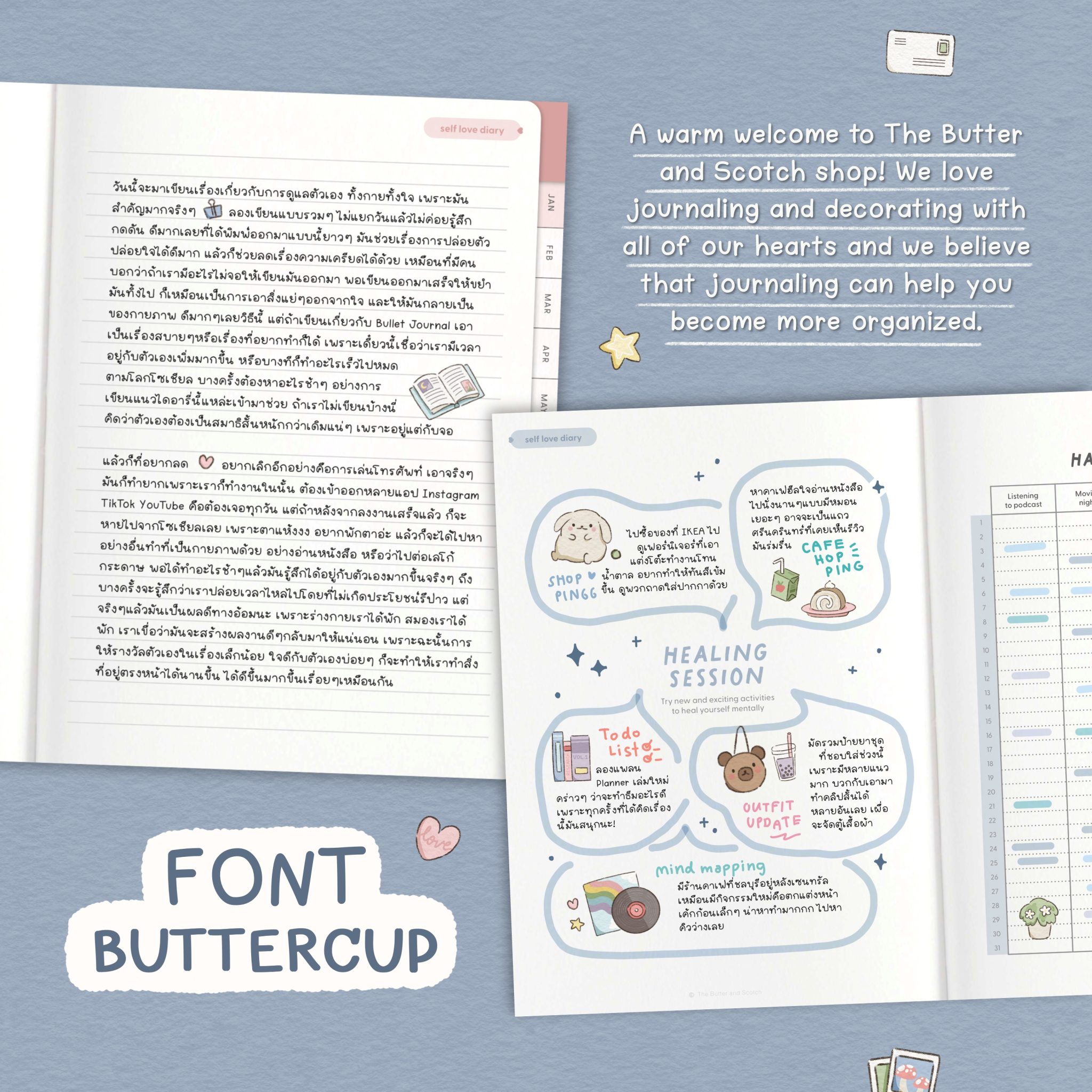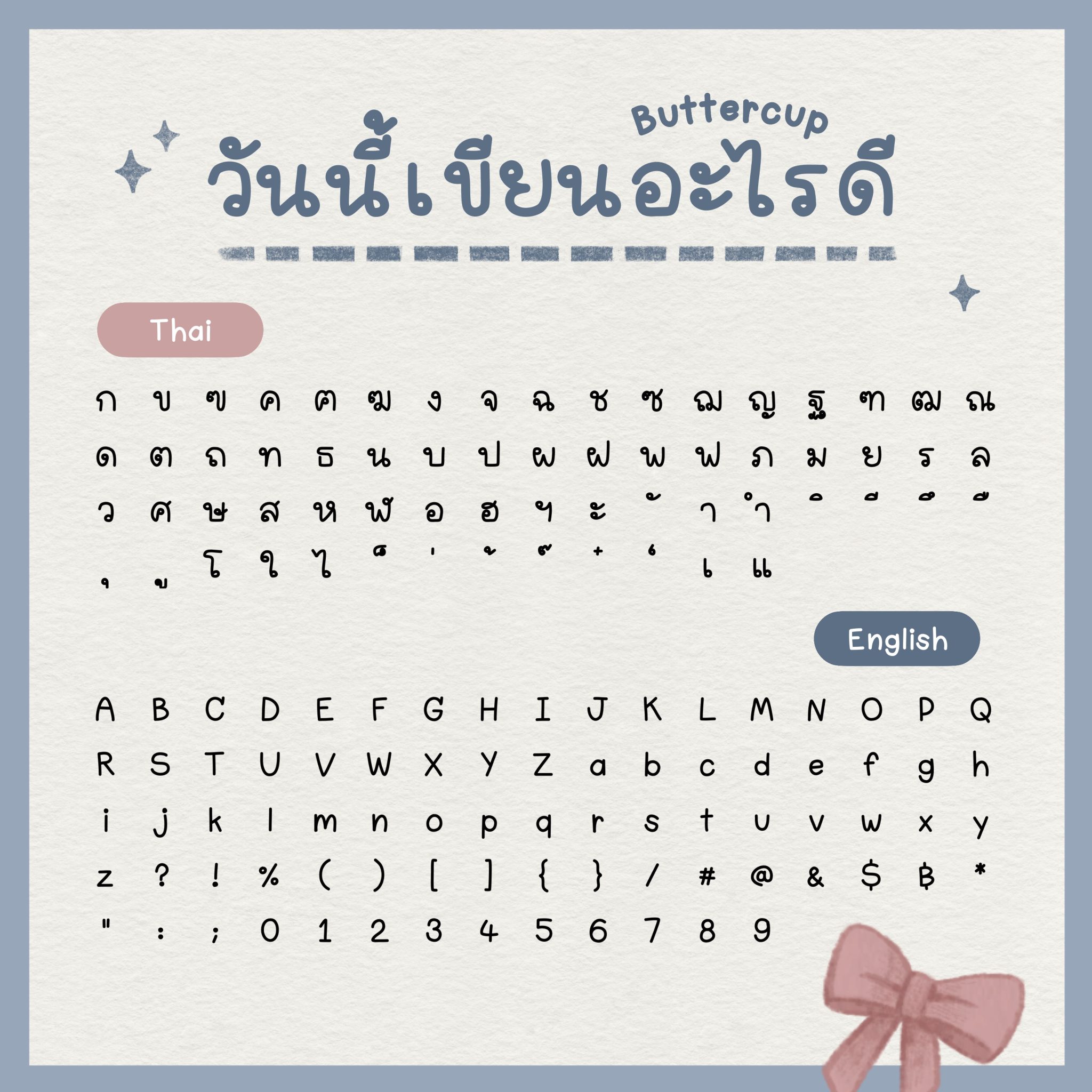
THE BUTTER AND SCOTCH | Font (Buttercup)
ฟอนต์ลายมือประจำร้าน The Butter and Scotch สไตล์น่ารักเรียบร้อย เป็นฟอนต์ที่ใช้ได้ในทุกๆวัน และช่วยให้การทำโน้ตของคุณน่าอ่